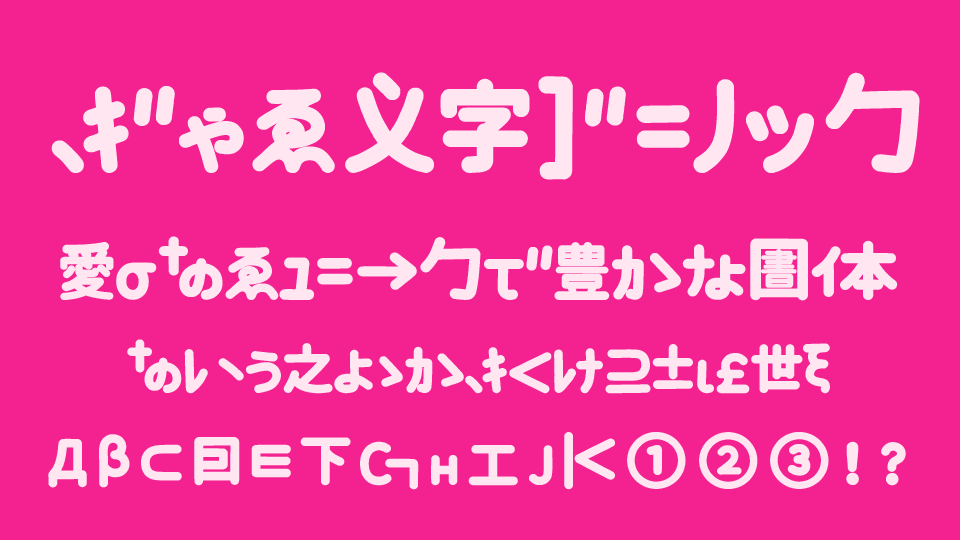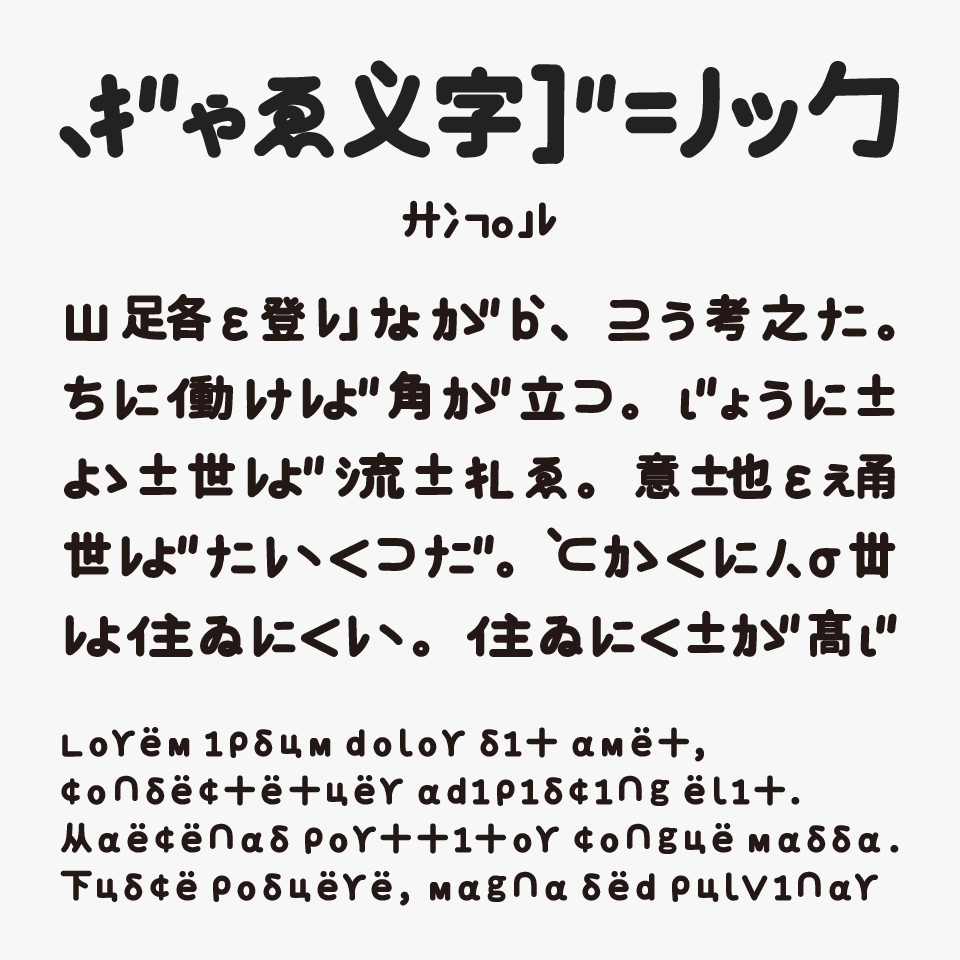
ぎゃる文字ゴシック
ぎゃる文字ゴシックフォントは、2000年代のギャル文字文化をゴシック体に落とし込んだ、平成レトロと遊び心が詰まったユニークなデザインゴシック体フォントです。
漢字の一部のパーツが記号や別の文字に置き換えられており、平成期にガラケーなどで流行ったギャル文字のように、一瞬では読めないような仕掛けが随所に散りばめられているフォントです。
プリクラ風・Y2K・ギャルカルチャー系のデザインや平成レトロなビジュアルなどあえてクセの強い世界観を演出したい表現にぴったりです。平成期を彷彿させる懐かしさと新鮮さが同時に押し寄せてくる、見ているだけでも楽しめるフォントです。